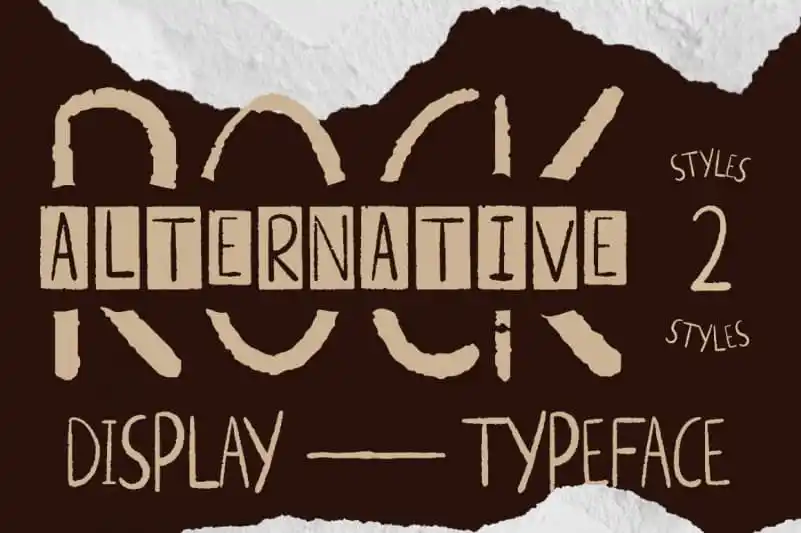
Alternative Rock Display Font – Download Grátis
A fonte ‘Alternative Rock Display Font’, criada pelo designer jetsmax, traz uma experiência visual vibrante para projetos decorativos e criativos. Inspirada nos ritmos de verão do rock alternativo que animam as festas musicais ao vivo, essa fonte artesanal enche os olhos com adrenalina, ideal para dar um empurrãozinho em qualquer projeto visual. Esta fonte é perfeita para aqueles que buscam uma maneira criativa de decorar e destacar seus projetos. Seja para assinaturas, logotipos ou até mesmo para design gráfico tradicional, ela traz energia e estilo para os mais variados usos. É a escolha certa para quem quer dar um tom vibrante e moderno às suas criações, sem sair da categoria de fontes decorativas. Com ‘Alternative Rock Display Font’, você pode transformar qualquer projeto em uma experiência visual cheia de vida e emoção, inspirada nas festas musicais que fazem dos verões tão especiais.